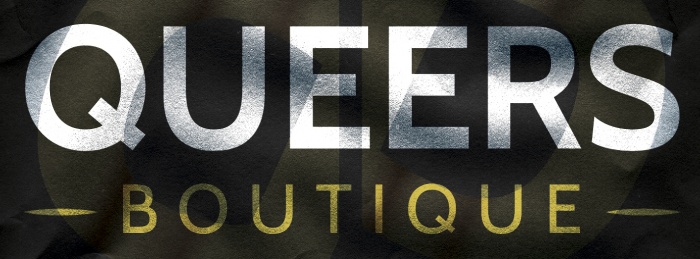
Schriftsuche anhand eines Bildes
ich habe wieder mal ein Schriftproblem.
Ich wurde gefragt, ob es mir möglich wäre, einen Flyer nach Vorgabe eines älteren zu gestalten. Nur leider ist das Layout bzgl der Typografie sehr dominant und es ist mir nur möglich, wenn ich die Schriftart habe. What the font konnte mir da auch nicht weiterhelfen also versuche ich es hier, da mir hier schon 2x erfolgreich weitergeholfen wurde.
Gotham und Museo Sans sind dicht dran, auch wenn sie Deine Schrift nicht genau treffen. Aber mit diesen Schriften könntest Du bei MyFonts & Co auf die Suche nach ähnlichen Schriften gehen – und auf diesem Umweg eventuell auf Deine Schrift stoßen.
WOW!!! Vielen Dank, die Cabin ist es! Wie erkennt man sowas? Echt krass!
gern geschehen. das etwas gurkige Q ließ mich freefont vermuten mit leichter tendenz zu google fonts (weil die zeichen insgesamt dann doch nicht so furchtbar sind). ›sort by popularity‹ war auch keine schlechte idee, denn da war sie dann schon auf platz 21.